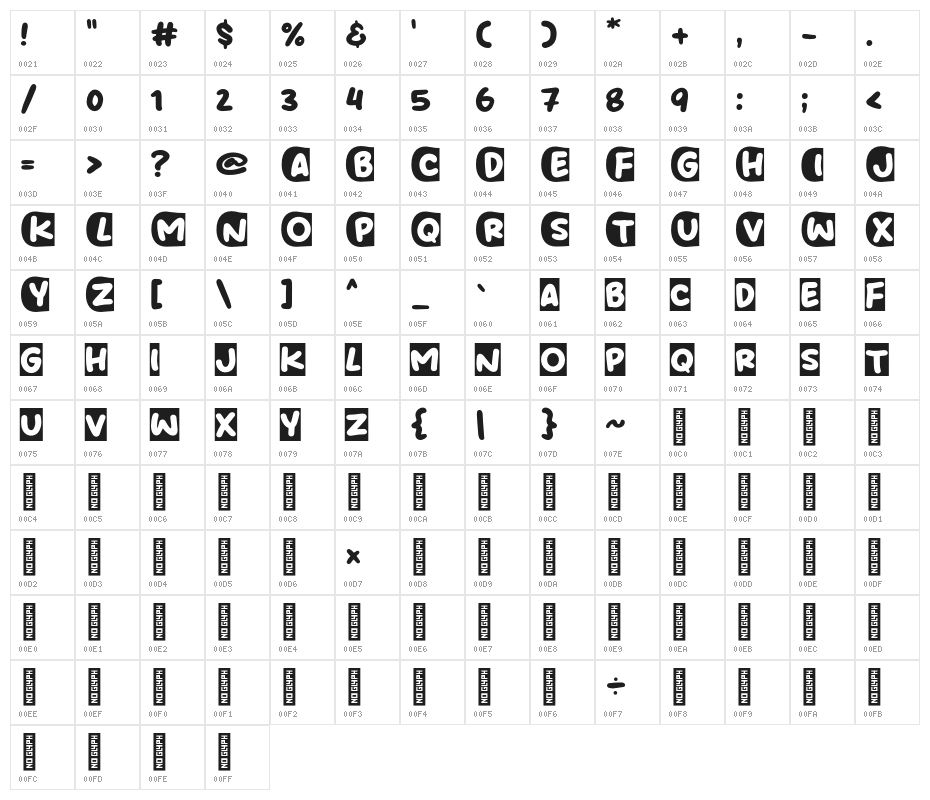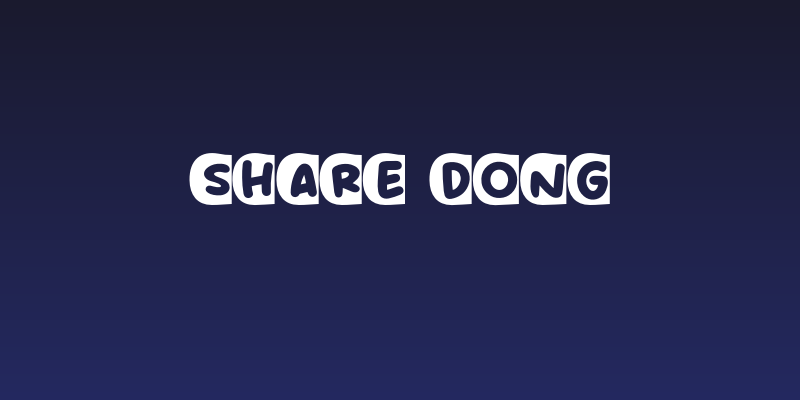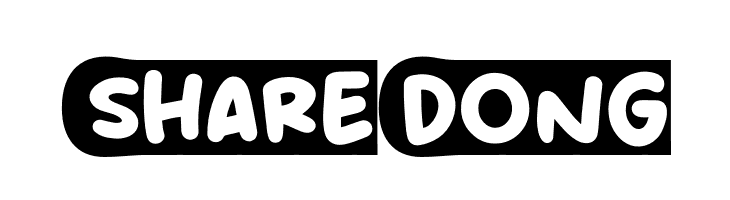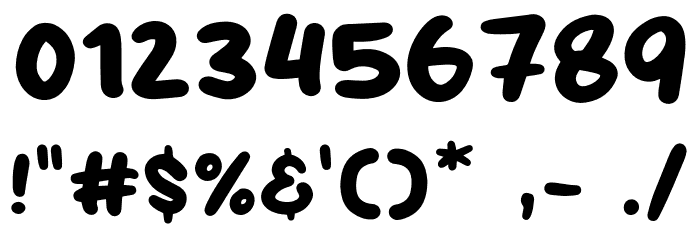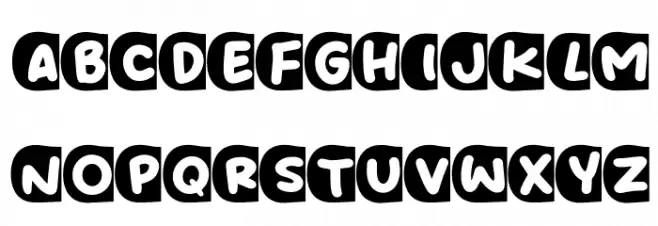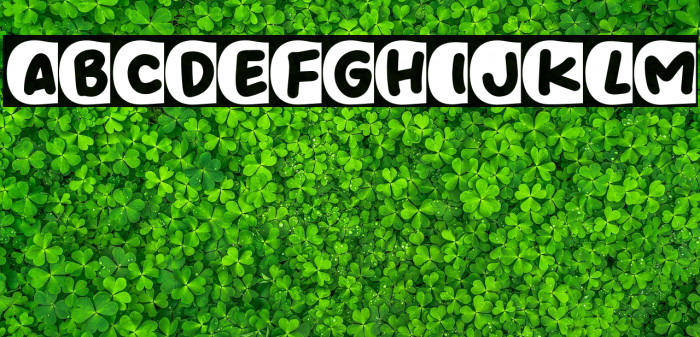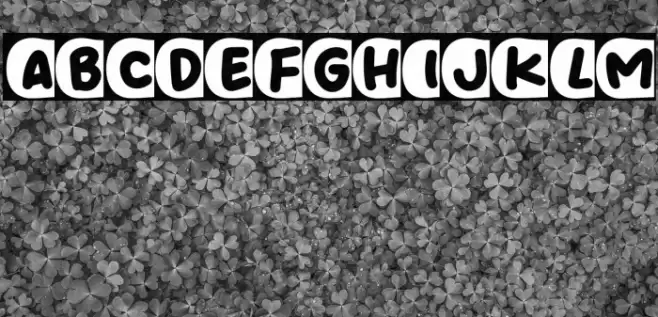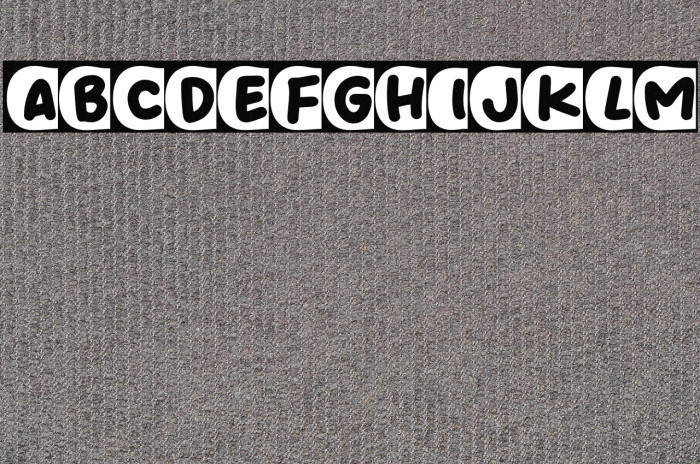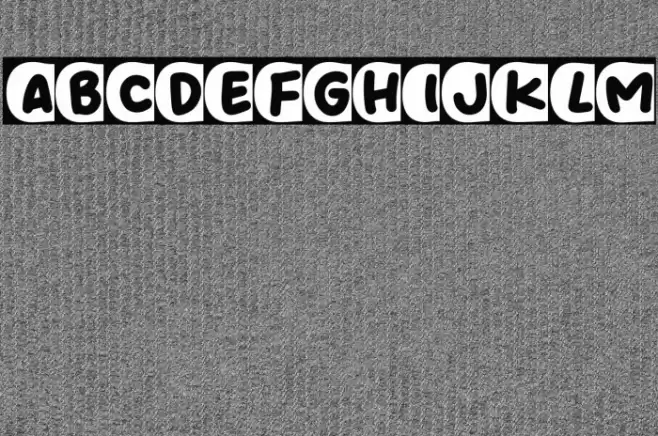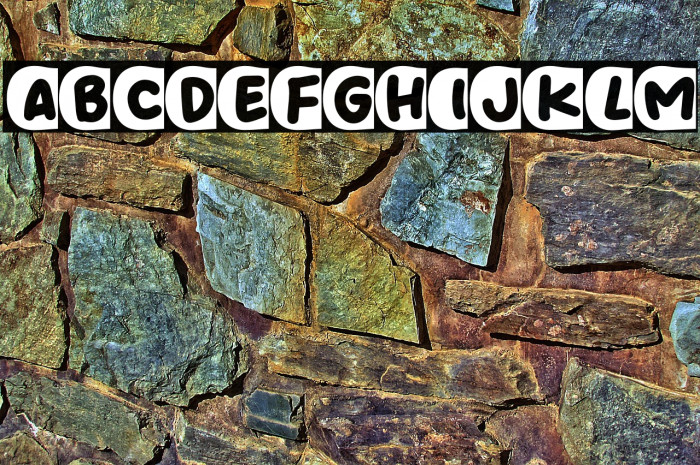
Share Dong Font
✎ Cartoon
| Catégories | Cartoon |
| Style général | Playful, Cartoonish |
| Projets proposés | Ideal for children's books, playful branding, comic strips, and party invitations. |